Khi thiết kế slide thì font chữ là một trong những thành phần quan trọng nhất mà chúng ta phải chú ý. Văn bản sẽ giúp bạn truyền tải nội dung đến người xem trong buổi thuyết trình. Tuy nhiên, nếu chỉ sử dụng những font chữ mặc định của Powerpoint thì sẽ khá nhàm chán và không tạo được sự khác biệt hay điểm nhấn. Bài viết dưới đây Gitiho sẽ tặng cho bạn đọc bộ sưu tập 1900+ font chữ cực đẹp dùng cho thiết kế Powerpoint trong file đính kèm của bài viết. Theo dõi nhé!
Bạn đã quá nhàm chán với những font chữ Times New Man hay Arial, bạn thấy bài thuyết trình của người khác có những font chữ khác lạ mà bạn tìm mãi trong Powerpoint vẫn không thấy có hoặc bị lỗi font, bạn muốn đổi mới slide của mình với font chữ nhưng lại không biết làm thế nào? Vậy thì những font chữ mà Gitiho cung cấp dưới đây chắc chắn sẽ hữu ích với bạn:
Bộ font chữ đẹp này chứa các phông chữ nét thanh, nét đậm với nhiều kiểu khác nhau mà bạn có thể áp dụng trong bất kỳ slide nào. Dưới đây là một mẫu font chữ nằm trong bộ font UTM:
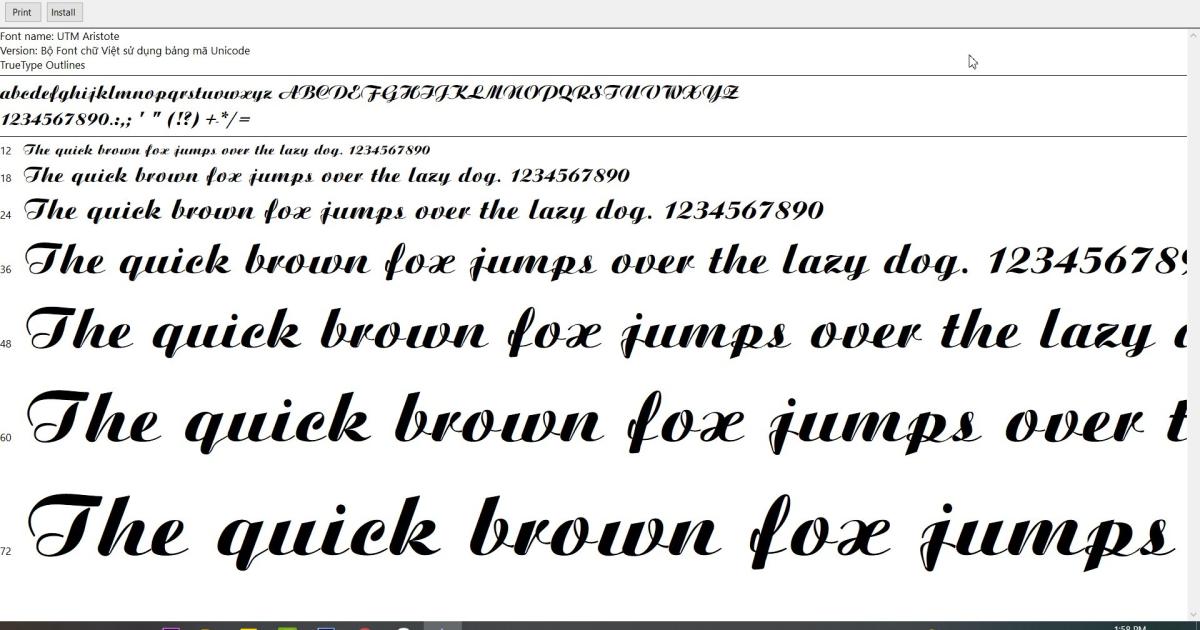
Font chữ iCiel được sử dụng rất rộng rãi trong giới thiết kế. Bộ font này có chứa rất nhiều kiểu chữ khác nhau từ hiện đại đến cổ điển, đơn giản hay phức tạp đều có. Điểm đáng chú ý là tất cả các font iCiel đều dễ đọc, đẹp mắt, tạo thiện cảm cho người xem. Có rất nhiều người thiết kế logo, sách, báo, infographic,... đều sử dụng font chữ iCiel.
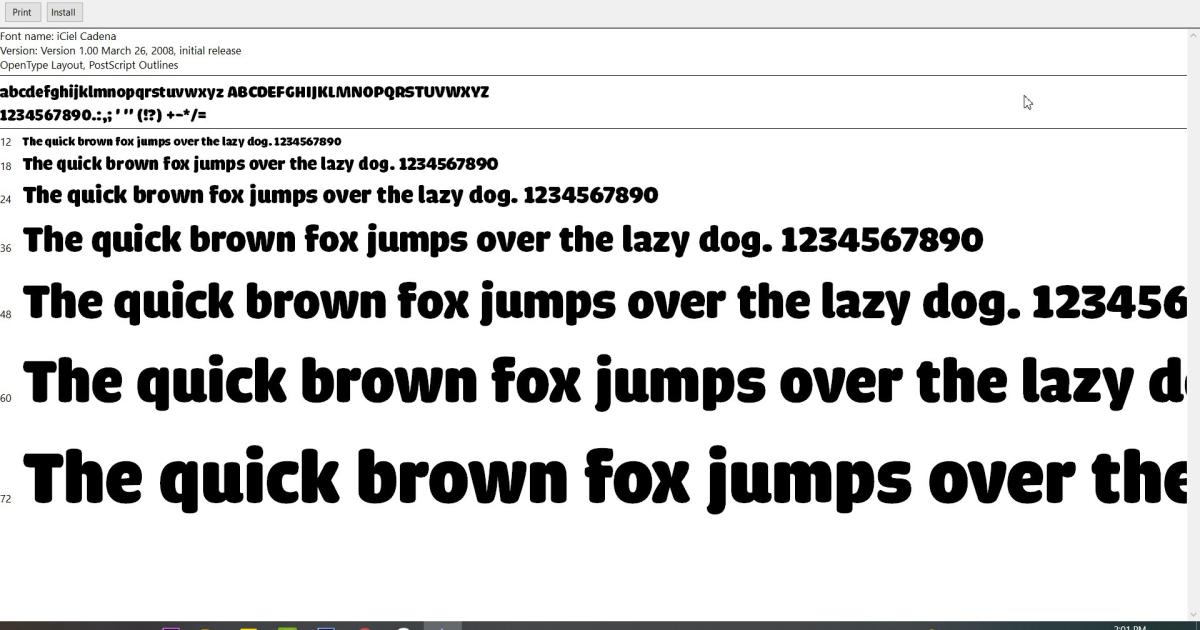
Bộ font chữ UVF hầu hết là kiểu chữ viết tay khá độc đáo. Font chữ này sẽ hỗ trợ cho bạn rất nhiều khi thiết kế các slide cần sự sáng tạo, tự do và vui nhộn.
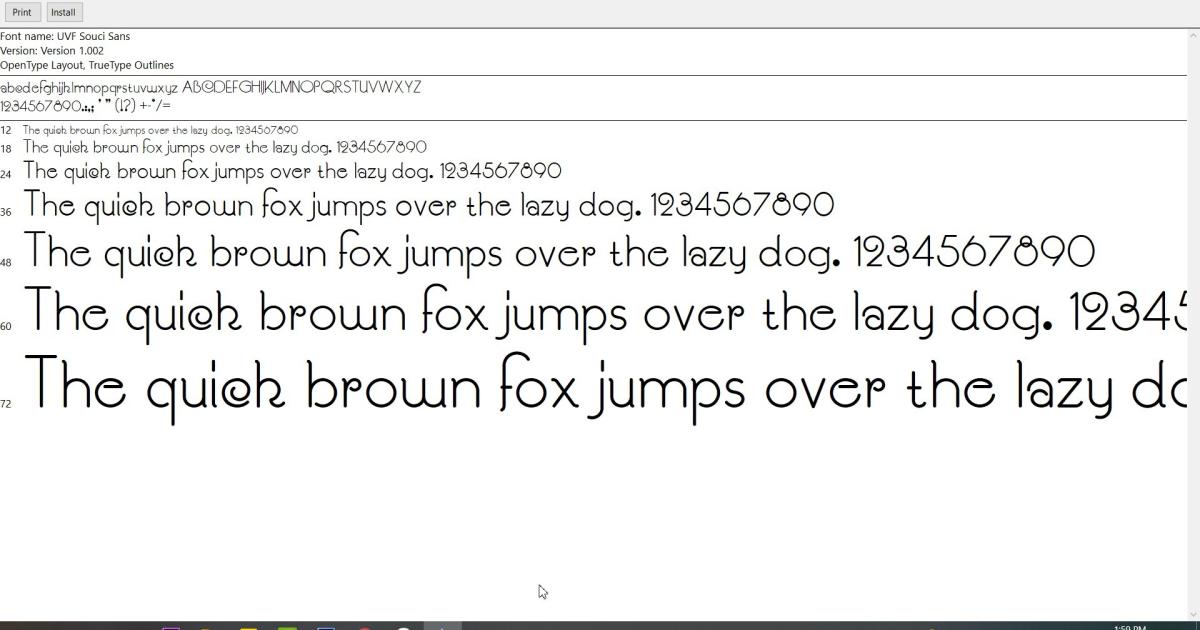
Nếu bạn cần font chữ đơn giản, chuyên nghiệp và dễ đọc thì hãy tìm các mẫu font chữ có tên bắt đầu bằng GMV. Hầu hết chúng đều đơn giản, có thể dùng cho nhiều loại nội dung thuyết trình khác nhau.
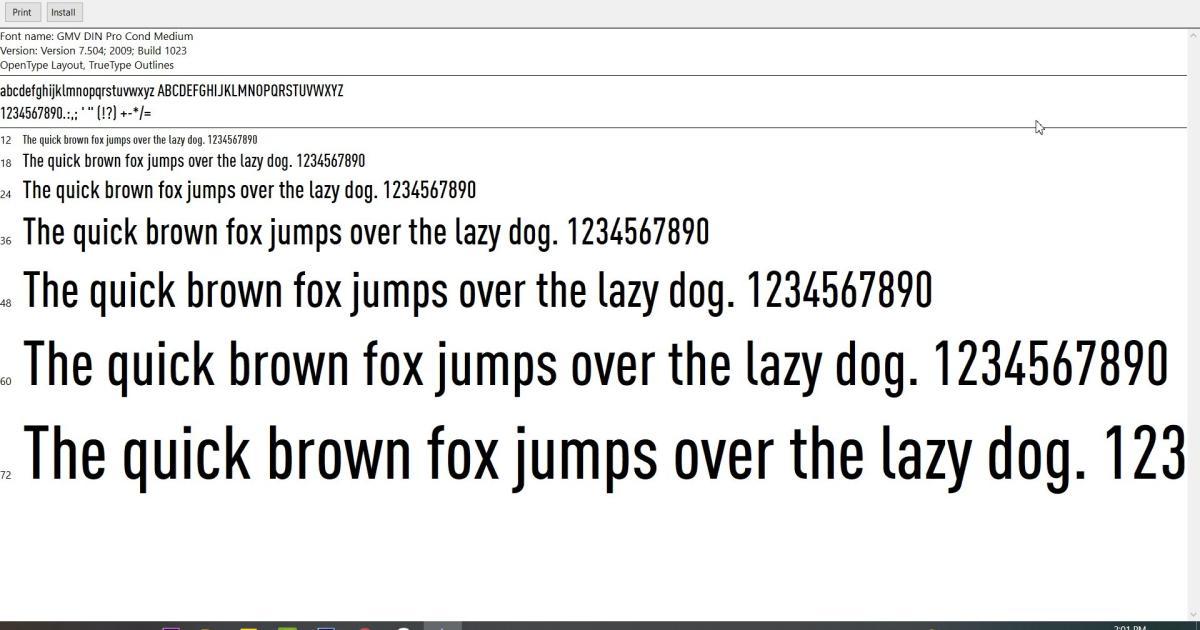
Trên đây chỉ là một vài font chữ đẹp Powerpoint được lựa chọn ngẫu nhiên để cung cấp cho các bạn bản xem trước. Hãy tải trọn bộ cả file về để khám phá nhiều font chữ Việt hóa ấn tượng hơn nhé. Khi sử dụng các bạn chỉ cần chú ý 4 điều dưới đây là có thể giúp slide Powerpoint trở nên chuyên nghiệp hơn:
Lựa chọn kiểu chữ phù hợp với chủ đề bài thuyết trình
Chỉnh cỡ chữ phù hợp với từng loại nội dung
Chọn màu chữ nổi bật trên màu nền của đối tượng phía dưới nó
Kết hợp vào bố trí chữ thật khoa học, hợp lý, không đặt chữ lộn xộn hay khó chịu cho người đọc